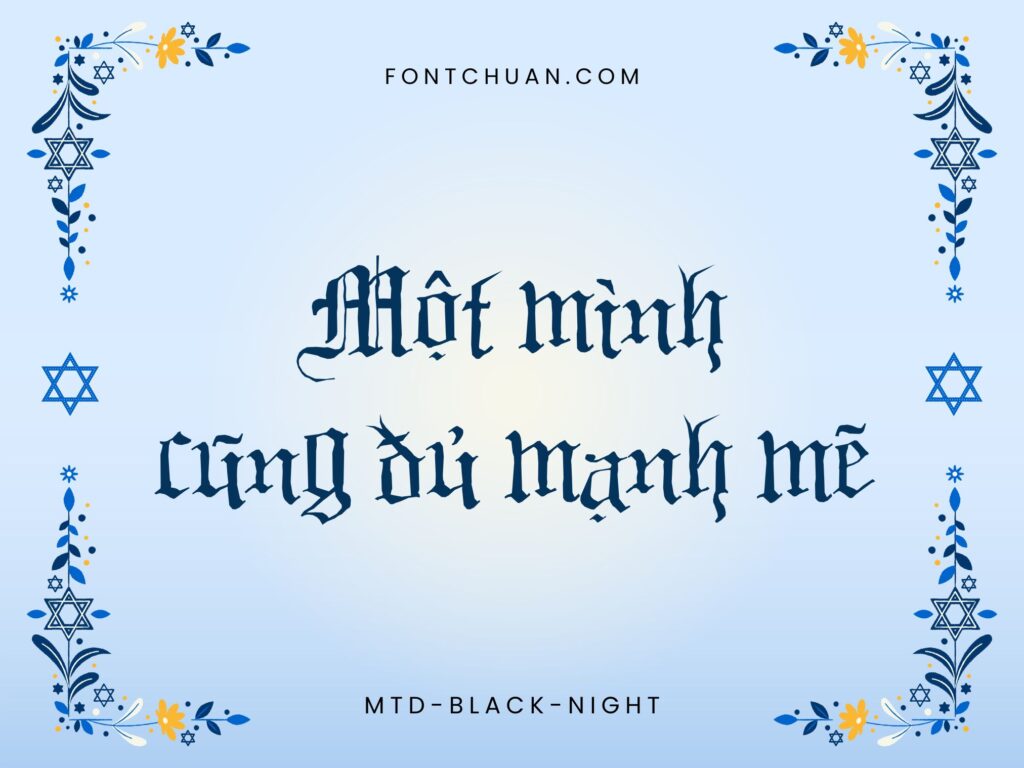
Font MTD Black Night Việt Hóa
Black Night là một Font chữ Halloween, được thiết kế bởi Blankids Studio. Với các đường nét độc đáo, hơi hướng kinh dị và chịu ảnh hưởng từ Font Gothic, font này tạo ra cảm giác bí ẩn và thu hút cho các thiết kế liên quan đến chủ đề Halloween. Để hỗ trợ cộng đồng thiết kế Việt Nam, Mộc Hạ đã Việt hóa font Black Night, giúp font này hỗ trợ đầy đủ tiếng Việt cùng hơn 200 ngôn ngữ khác. Phiên bản Black Night Việt hóa đã được thành viên Font Chuẩn sưu tầm và đăng tải, nhằm mang đến sự lựa chọn phong phú hơn cho các nhà thiết kế.
Về đặc điểm thiết kế, Black Night sở hữu các ký tự với nét vẽ tay độc đáo, tạo nên sự khác biệt và ấn tượng mạnh mẽ. Font này rất phù hợp cho các thiết kế liên quan đến tiêu đề, poster, logo, bao bì sản phẩm và các dự án sáng tạo khác, đặc biệt là trong các sự kiện như Halloween và các lễ hội. Ngoài ra, Black Night cũng là một lựa chọn lý tưởng cho các ngành nghề như quảng cáo và giáo dục, mang đến phong cách độc đáo và thu hút.